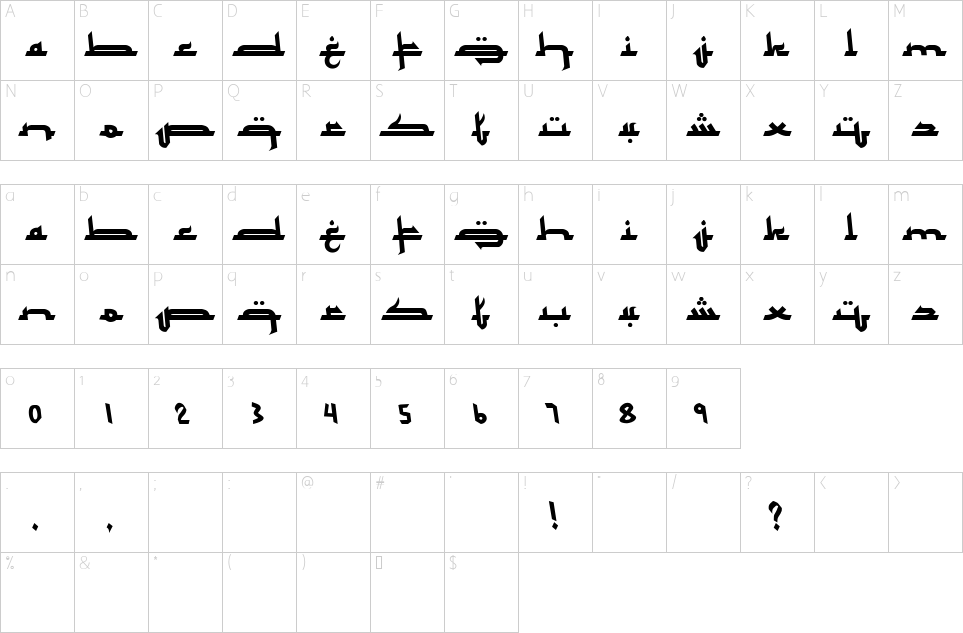
A fonte Mukadimah é uma opção ótima para projetistas de gráficos que buscam uma fonte moderna e versátil. Desenvolvida por Adien Gunarta, esta fonte está disponível para download tanto em Windows quanto em Mac. Com seu design clean e minimalista, Mukadimah pode ser facilmente adaptada para um número de aplicações, desde design gráfico até criação de sites. Mais impressionante, esta fonte gratuita já foi baixada 15,948 vezes, o que demonstra seu valor e popularidade entre criadores de design. Se você está procurando uma fonte versátil e estilosa, Mukadimah é uma escolha inteligente para qualquer projeto.